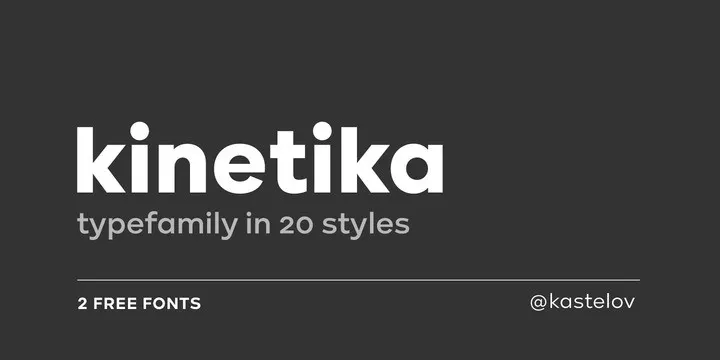
Kinetika Sans Serif Font – Download Grátis
Kinetika Sans Serif é uma família elegante de fontes geométricas sem serif que combina delicadeza clássica com ritmos modernos dos caracteres para atender a qualquer trabalho de design. Esta font foi criada e compartilhada por Kastelov, trazendo 20 pesos variando desde tipos retos até suas correspondentes itálicas. Seu design geométrico permite uma flexibilidade impecável em diversos ambientes digitais, seja para criar um texto minimalista e clean em sites ou para adicionar um toque de sofisticação a elementos gráficos. A Kinetika Sans Serif é a escolha perfeita para designers que buscam equilíbrio entre elegância e modernidade, oferecendo uma maneira única de expressar ideias visuais com grande precisão e estilo.